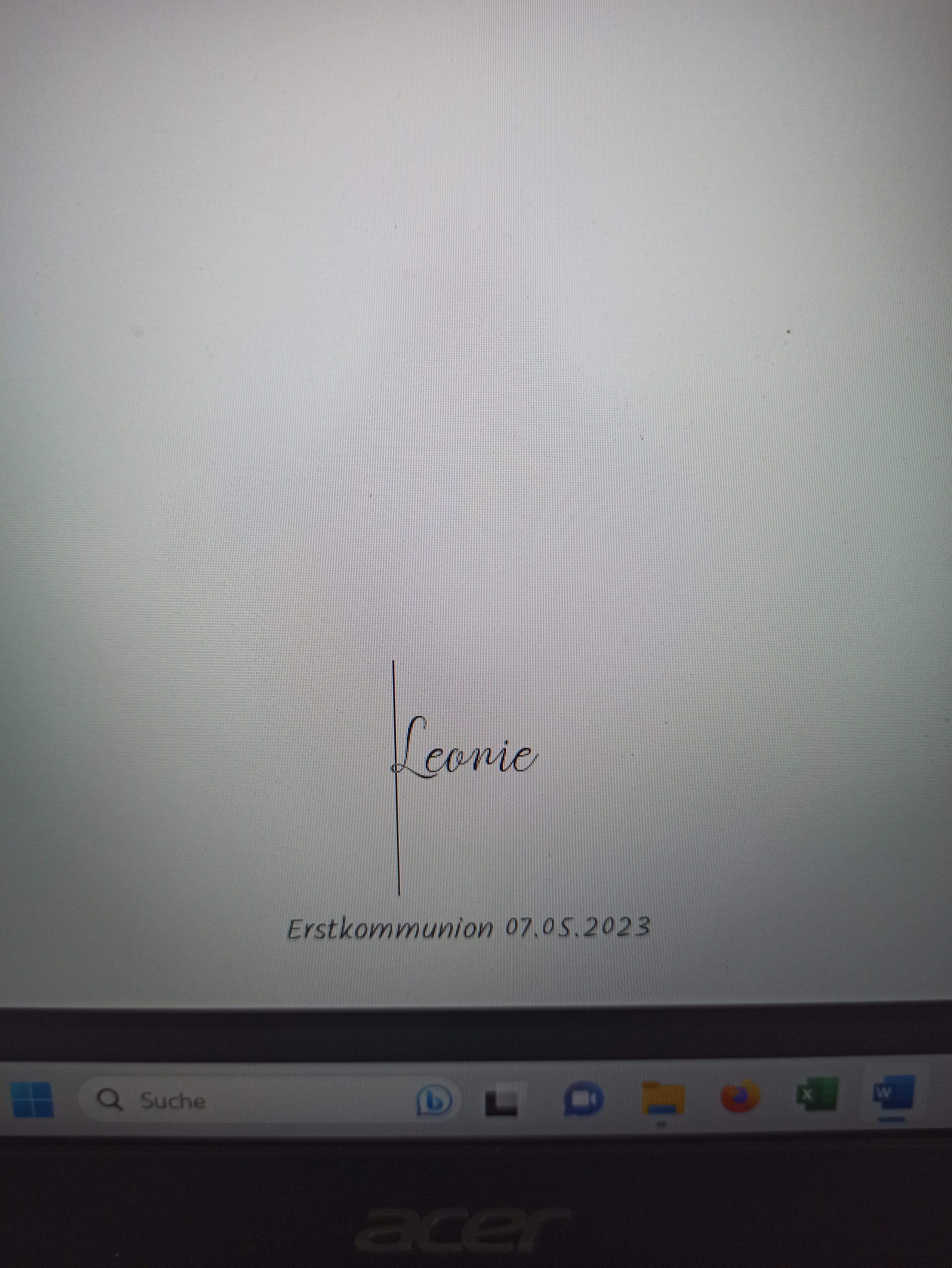
Schriftarten dicht untereinander Word
Ich habe mir einige neue Schriftarten herrunterladen. Ich arbeite in Word. Wenn ich jetzt mit einer Schriftart ein Wort schreibe was ich relativ groß stelle wird der Abstand zur nächsten Zeile sehr groß( 3 cm). Das Wort lässt sich auch nicht zum unteren Rand verschieben ohne auf die zweite Seite zu springen. Ich möchte ein Wort mit der großen Schriftart und direkt darunter eine andere kleinere Schriftart. Bei Powerpoint ist das kein Problem. Geht das auch in Word ?
Bei <Return> erzeugt Word einen neuen Absatz. Für eine neue Zeile mußt du <Shift>+<Return> betätigen.
Ich vermute auch, Du hast die Abstandsoptionen zu groß eingestellt. Ändern kannst Du das hier:
Setze einfach einen "genauen" Zeilenabstand in den Absatzeinstellungen. Dann spielt die Größe der Schruft keine Rolle mehr für den Zeilenabstand.
Funktioniert leider auch nicht. Wenn ich die große Schriftart markiere wird das Feld auch wesentlich größer angezeigt als die Schrift wirklich in der Höhe ist . Uns so groß ist auch der Abstand.
Wenn der Tipp von Pete11 nicht hilft, mach doch mal einen Screenshot wie es aussieht und am besten auch die Zeilenabstandsoptionen von dem zu großen Absatz anzeigen lassen und hier auch Posten.
So ist das hier nur Rätselraten.
Seltsam. Wenn ich im Absatzormatdialog bei Zeilenabstand "genau" statt "einfach" auswähle, spiet die Zeichengröße keine Rolle mehr.
Kannst mir ja ein Stück des Dokumentes schicken, da schau ich nach.
Das Problem scheint an der Schriftart zu liegen. Bei anderen Schriften ist es nicht so. Sie wird in der Liste winzig klein angezeigt. Im Dokument habe ich sie dann auf Größe 48 gestellt.
derFireBird hatte doch geschrieben, was in einem Screenshot zu sehen sein soll. Warum nur dieser Ausschnitt?
Ich vermute aber angesichts des riesigen Cursors: Die Schriftart ist in sich sehr klein und bedarf eines extrem großen Schriftgrads, um überhaupt sichtbar zu sein. Wechsle mal die Schriftart von "Leonie" in eine Standardschrift. Sollte die dann deutlich größer erscheinen, bedeutet das: Die Schrift taugt nix, nimm was Richtiges.
Ja es stimmt. Sie ist sehr klein. Aber in Powerpoint wäre es ja machbar. Gibt es irgendwelche Nachteile wenn man es statt in Word in Powerpoint schreibt und anschließend druckt?
Ich wüsste nicht, was an der Textfunktion von PP soviel anders ist, dass es zu diesen Unterschieden käme.
PP ist eh besser für Grußkarten etc. geeignet.
Aber warum nimmst Du überhaupt so eine verkorkste Schrift?
Sie gefiel mir halt. Bei Powerpoint kann man nur im Textfeld was man vorher einfügt , schreiben. Richtig? Wie bekomme ich das ganze Textfeld mittig, also zentriert?
Schieben. 😉 Mitte wäre nur zentrierter Text in einer Textbox (Textfelder gehören ins Kapitel Formulare) die bis an die Seitenenden reicht. Ach ja, siehe unten!
Fonts sind immer knippig. Selbst zu versuchen mit (negativen) Absatzabständen Unterlängen und geplanten Platz aufzufangen wird zum Horrortrip.
Die Textboxen dürften die einzige Lösung sein. Oder analog PP mit dem was WordArt genannt wird Zeilen (Raster ausschalten!!) genau zu platzieren.
Hm, man erkennt zwar leider nicht ganz so viel, aber ja, sieht wirklich nach einem verkorksten Schriftbild aus.
Also entweder andere Schrift suchen (gibt viele verschnörkelte)
oder als Workaround - wenn man bei Word und der Schrift bleiben will - wie cumulonimbus8 schon geschrieben hat:
z.B. das "Leonie" in eine Textbox setzen, die kannst du dann hinter den anderen Text schieben, sodass der Freiraum eben dort hinter verschwindet. Oder andersherum; die untere Zeile in eine Textbox, die du vor den anderen Text nach oben schiebst.
Ausrichtung, Zentrierungsoptionen, etc. findet man dann alles in den Formatierungstools.
Doch.
MS Office ist ein zusammegekaufter Haufen Software von verschiedenen Ursprungsfirmen, der dann im Laufe der Jahre auf so ein ähnliches Äußeres getrimmt wurde von Microsoft.
Bei Excel sieht man es am besten, wenn man die VBA Programmierung öffnet.
Da werden völlig andere Variablenbezeichnungen geführt, wie bei Word zum Beispiel.
Powerpoint hieß früher Presenter von der Firma Forethought.
G.O.Tuhls schrieb:
PP ist eh besser für Grußkarten etc. geeignet.
Njet.
Man kann damit auch feine andere Sachen machen.
Die Schriftausrichtung geht am besten über Textboxen, wie bei Word übrigens auch.
Das Bild sagt viel über die Ausrichtungsmöglichkeiten in Textboxen:
Die dünne schwarze Strichlinie -------- besagt, daß ein Feld zentriert zur Seite ausgerichtet ist.